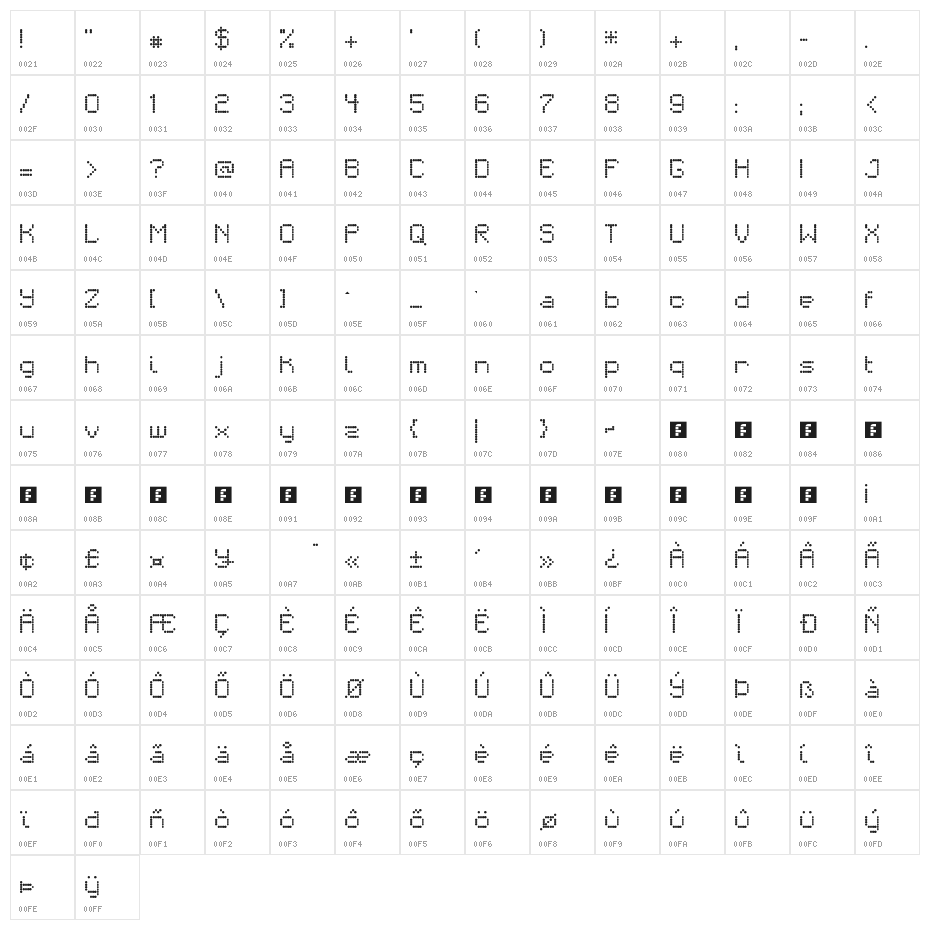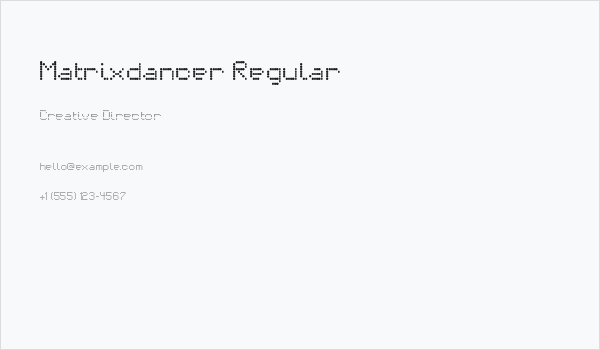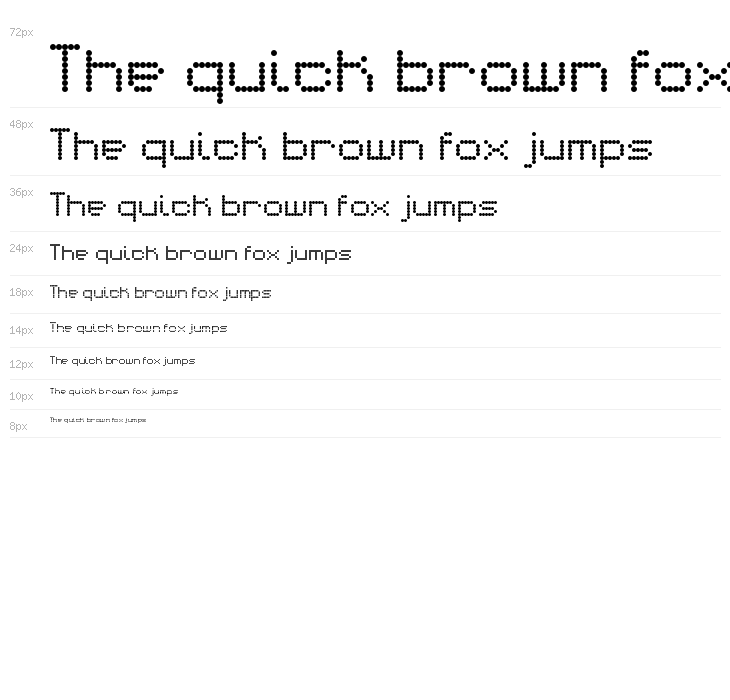
Matrixdancer Regular Font
| Caso d'uso | Headlines, Logos, Digital displays |
| Progetti proposti | Ideal for digital displays, tech-themed posters, futuristic branding, or any project requiring a modern, digital look. |